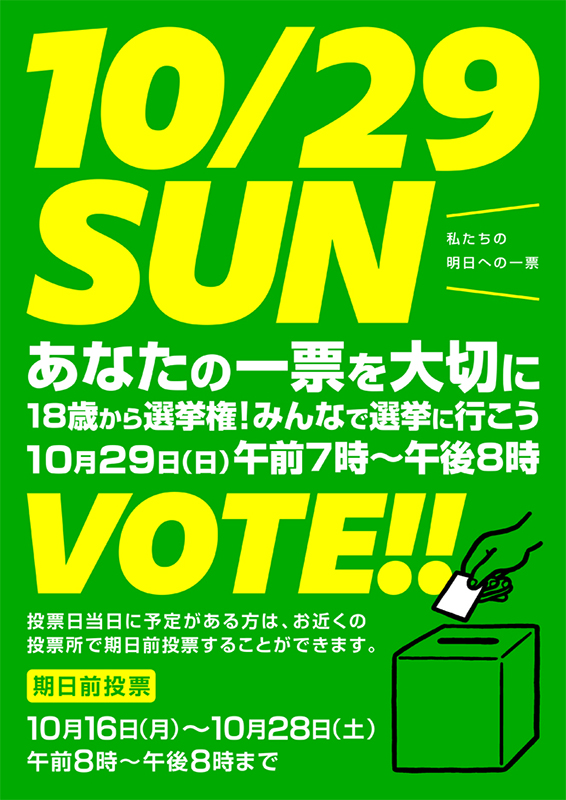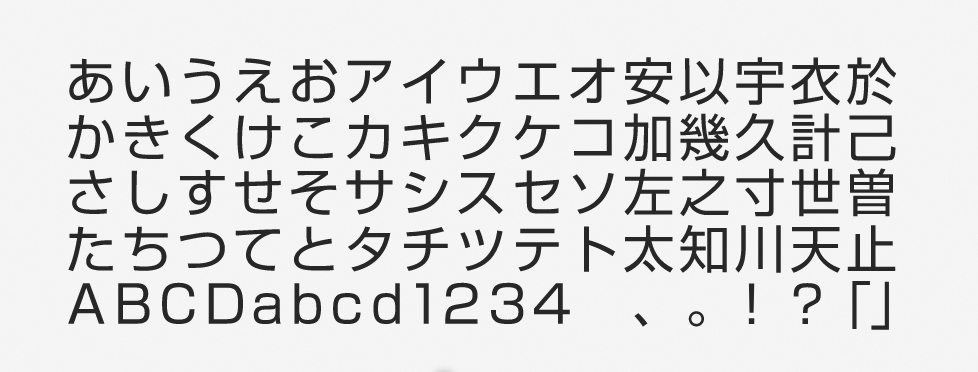
※作例内の欧文は「Sharoa Pro Ultra Italic」を使用
「新ゴ」について
新ゴはプロのデザイナーにも愛用されている定番のゴシック体です。汎用性が高く、印刷物から広告、グラフィックデザイン、サインやディスプレイまで、幅広く活用できます。現代的かつシステマチックな雰囲気で、縦組みでも横組みでもOK。インパクトのある大きな文字はもちろん、小さなサイズの文字列で使っても可読性が損なわれません。
「新ゴ」の特徴
新ゴは装飾を削ぎ落とした均質なフォントです。明るい雰囲気を持ち、すっきりと現代的な印象を与えることができます。見やすさと読みやすさを兼ね備えていることも大きな魅力。ウエイトのバリエーションも多く、扱いやすい書体です。
さらに、それぞれの文字を構成するエレメントで、水平や垂直の線が多いことも特徴。これにより、文字列を組んだときに整然としたラインが生まれます。抑揚を出すというよりは、スマートに仕上げたいときに最適です。
新ゴは「国内の風景を作っている」と表現しても過言ではない日本を代表するゴシック体です。「超」がつくほどの安定感があります。作例では「あなた」と「の」など、仮名の文字サイズに変化を加えました。こうすることで、平坦な印象を避けて読み進める際のリズム感も出せます。